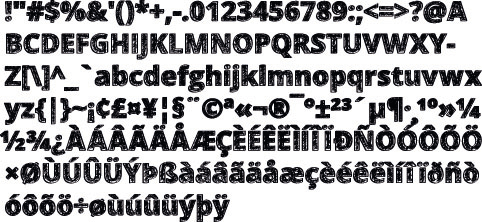
Wer kennt den Ursprung dieses "Entwurfs"?
Bekomme gerade von einem Kursteilnehmer unten abgebildeten Entwurf. Er behauptet ihn selbst entworfen zu haben. Hhhhmmmm ... kennt einer zufällig einen sehr "ähnlichen" Font von euch? Die Kievit ist es nicht.
Vom Man zum Lion: Solche Studenten braucht der Mann. Sehr witzig. Aber der Open Sans ist es nicht glaube ich, allerdings gebe ich meine rechterhand dafür das das Ding durchgepaust ist oder wieviele Jahre hat der Kursteilnehmer daran "gearbeitet"?
Weil?
!1elf
Das ist jetzt ein kleines Rätsel. Habe ich Dich damit auf dem falschen Fuss erwischt? (Das ist eine Anspielung.) Und dann war da noch die Sache mit den 3 Ecken ... ich könnte da noch weiter gehen
Spekulatius: Vielleicht hat da einer die Droid Sans Bold genommen und dem I das Leben auf großem Fuß verboten?
Was meinst du? 1, 3, g seien anders? Kann da keine Unterschiede erkennen. Wo wären die?
Oh nein! Ich habe da was verwexelt! PT-Sans ... Miſt, ich werde alt. Bitte ſtreiche meine Antwort aus dem Protokol. *rotwerd*